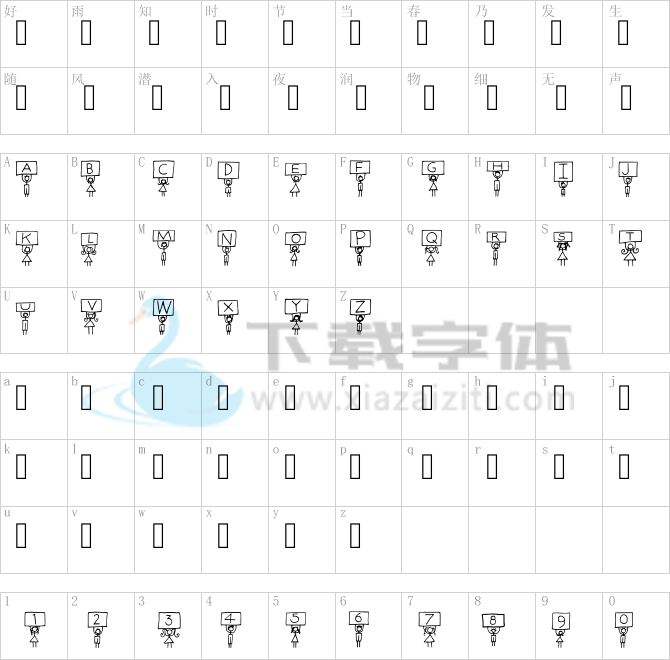
Alpha Kids.ttf字体下载,这款字体结构工整、笔画清晰,兼顾美观与易读性,适用于标题、正文、海报、包装、LOGO 等多种场景。字形优雅稳定,风格百搭耐看,适配日常排版与创意设计,让文字呈现更舒适、更具质感。Alpha Kids.ttf字体下载一笔一画,皆是细节,以均衡的比例、流畅的线条打造舒适视觉体验,字形端正大气,风格简约现代。无论是商业设计、品牌宣传还是日常排版,都能轻松驾驭,让文字更有格调与力量。Alpha Kids.ttf字体下载字体下载。